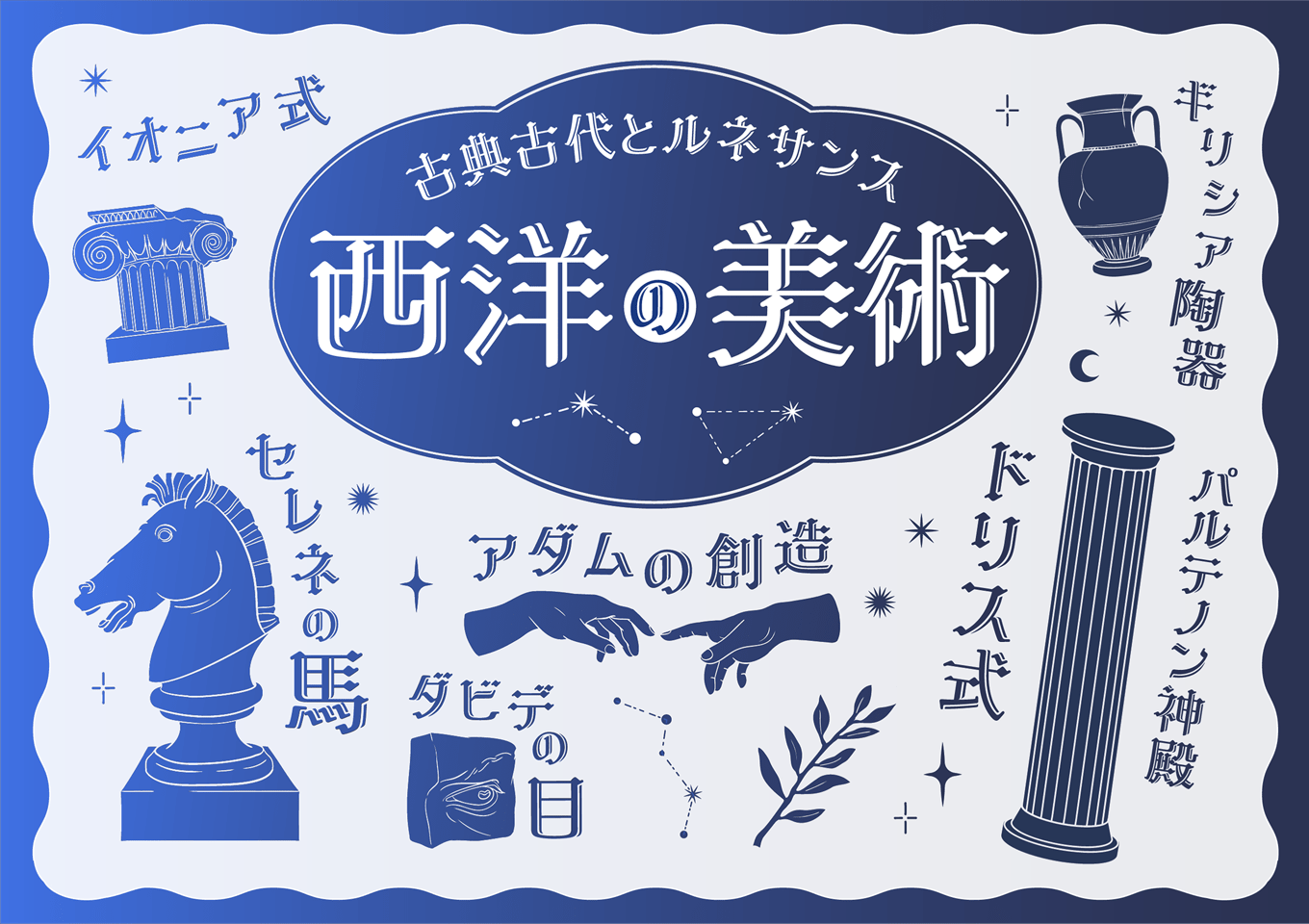
タイプバンクブランドのかな書体「TBかナ-白のアリス」に漢字を追加した、レトロモダンなデザイン書体です。平筆由来の西洋風ストロークとクリアで柔らかなエレメントをもつ「赤のアリス」にラインを入れることにより、さらに装飾性を高めた書体です。ゲームやコミックの表紙など、見出しやキャプションなどで華やかな可愛らしさを演出したい際に最適です。